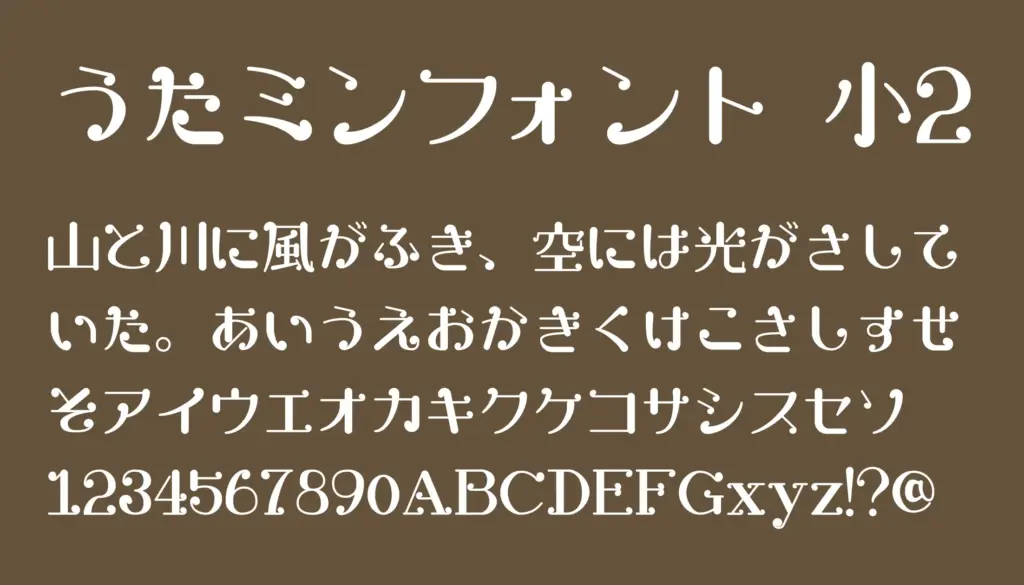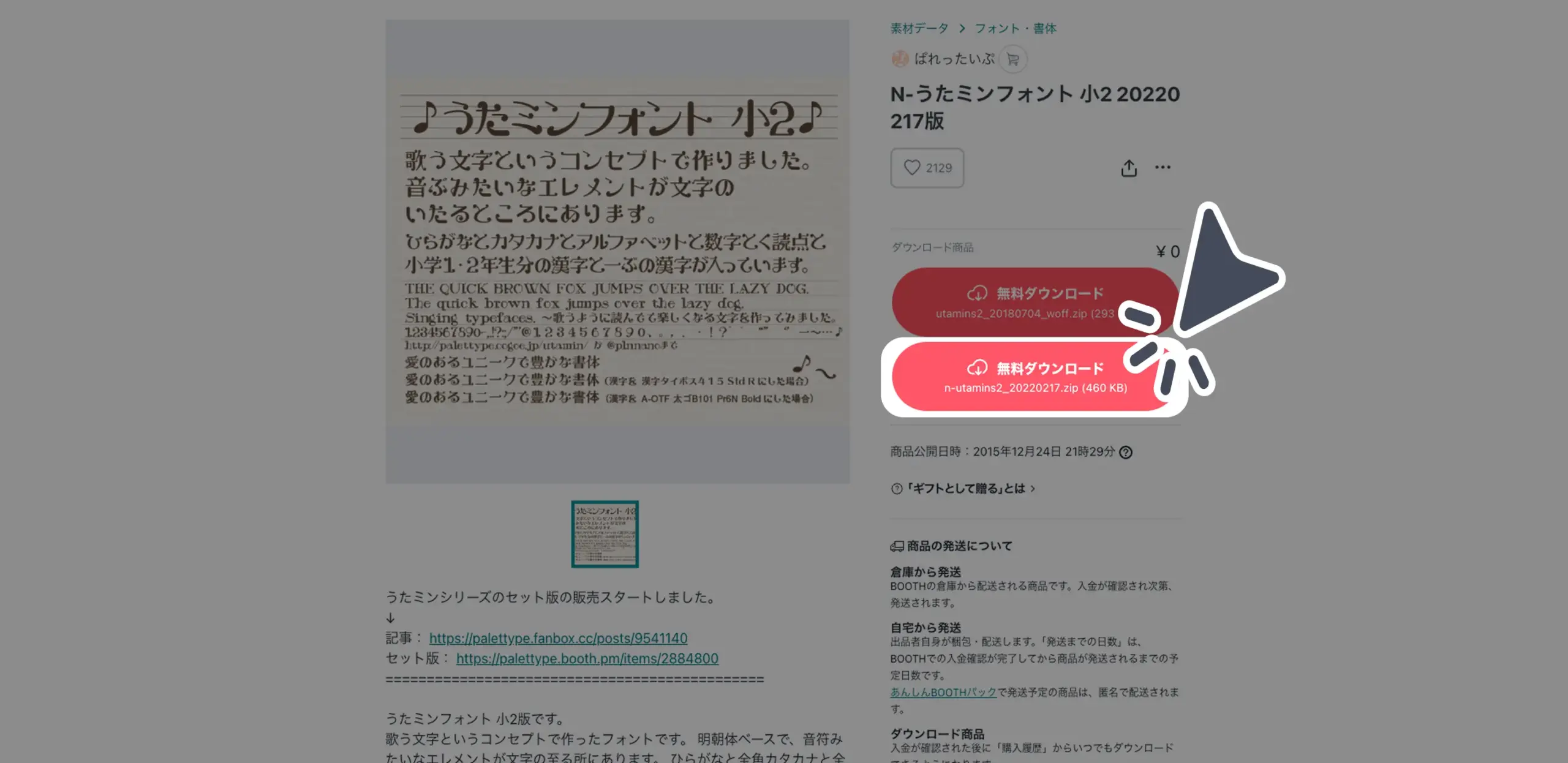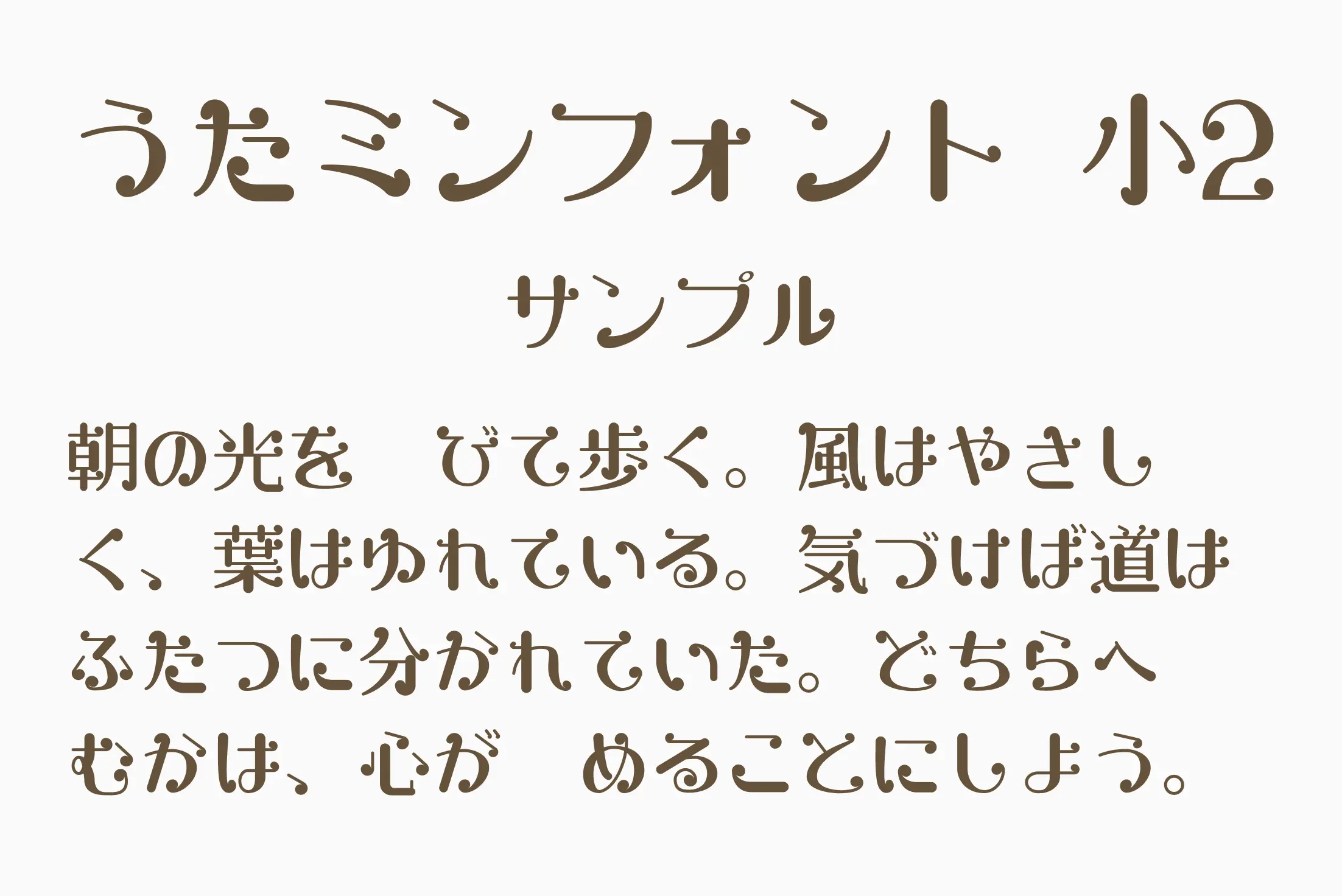
“歌う文字”をコンセプトにした明朝体ベースの日本語フォントです。文字の隅々に小さな音符の装飾が散りばめられており、ポップでエレガントな印象を与えます。ひらがな・カタカナ・全角数字・句読点に加え、小学2年生程度の漢字まで収録されており、子供向けデザインやグリーティングカード、動画の歌詞表示などにぴったり。
うたミンフォント 小2